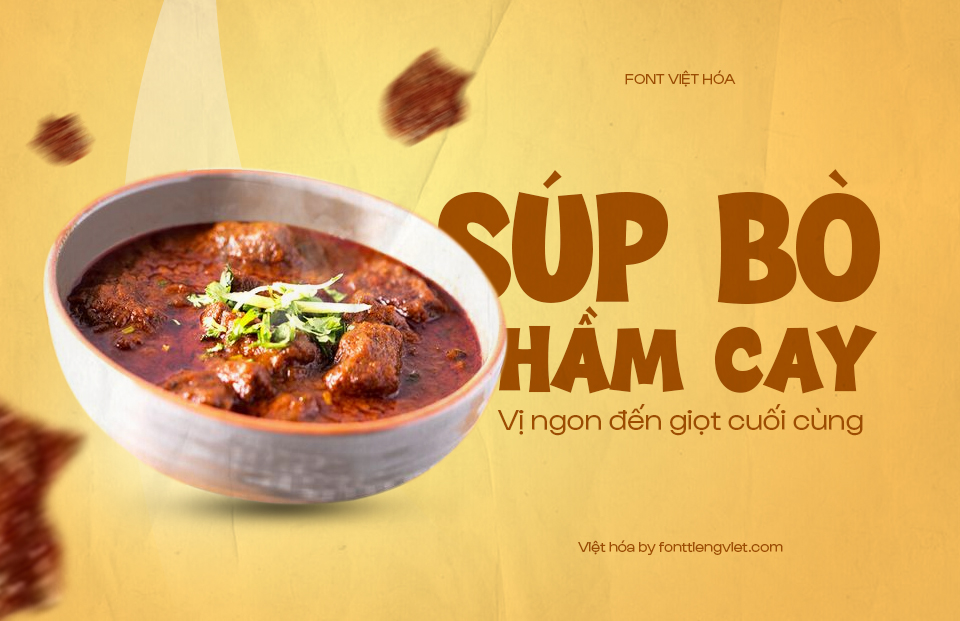
Giới thiệu về Font Việt hóa 1FTV VIP Comic Jungle
Trong thế giới đồ họa hiện đại, việc tìm kiếm một bộ Font Chữ độc đáo và ấn tượng luôn là ưu tiên hàng đầu của các nhà thiết kế. Font Việt hóa 1FTV VIP Comic Jungle là một lựa chọn hoàn hảo dành cho những ai yêu thích phong cách năng động, vui nhộn và đậm chất phiêu lưu. Được lấy cảm hứng từ các bộ truyện tranh kinh điển, phông chữ này mang đến sự phá cách mạnh mẽ nhưng vẫn đảm bảo tính thẩm mỹ cao cho mọi tác phẩm.
Ưu điểm nổi bật của Font Việt hóa 1FTV VIP Comic Jungle
Đặc điểm lớn nhất của bộ font này chính là các đường nét dày dặn, bo tròn mềm mại tạo cảm giác gần gũi. Font Việt hóa 1FTV VIP Comic Jungle đã được tinh chỉnh kỹ lưỡng về dấu tiếng Việt, giúp người dùng không còn gặp lỗi hiển thị khi soạn thảo nội dung. Với cấu trúc chữ cái sáng tạo, nó cực kỳ phù hợp cho các tiêu đề lớn, banner quảng cáo hay những hình ảnh minh họa dành cho trẻ em và học sinh trong trường học.
Ứng dụng thực tế của phông chữ trong giáo dục và thiết kế
Bộ font này không chỉ dừng lại ở các dự án thương mại mà còn ứng dụng rộng rãi trong môi trường giáo dục. Giáo viên có thể sử dụng để làm giáo án điện tử sinh động, còn học sinh dùng để trang trí báo tường hoặc làm Slide thuyết trình. Sự linh hoạt giúp Font Việt hóa 1FTV VIP Comic Jungle trở nên phổ biến tại Việt Nam.
Lưu ý khi sử dụng bộ font này
Để đạt hiệu quả tốt nhất, bạn nên kết hợp font chữ này với các tông màu rực rỡ như cam, xanh lá hoặc vàng. Điều này giúp tôn vinh tinh thần “rừng xanh” mà bộ font hướng tới, tạo nên sự đồng nhất cho bản thiết kế.
Kết luận về bộ phông chữ Comic Jungle